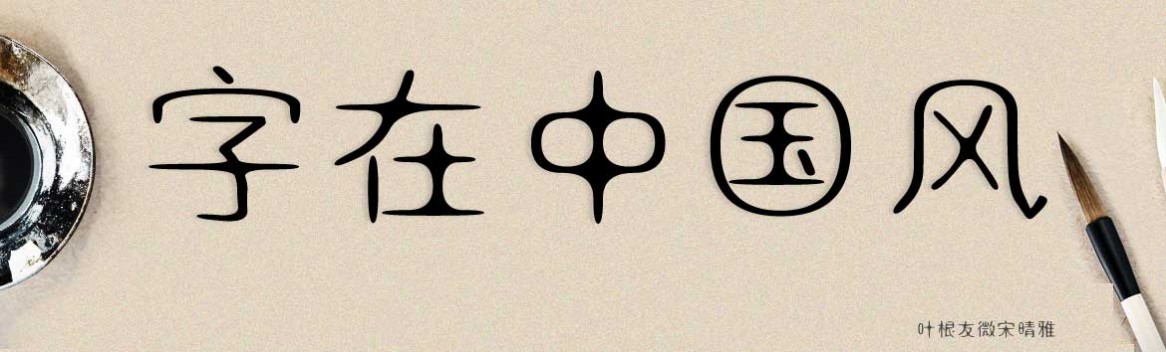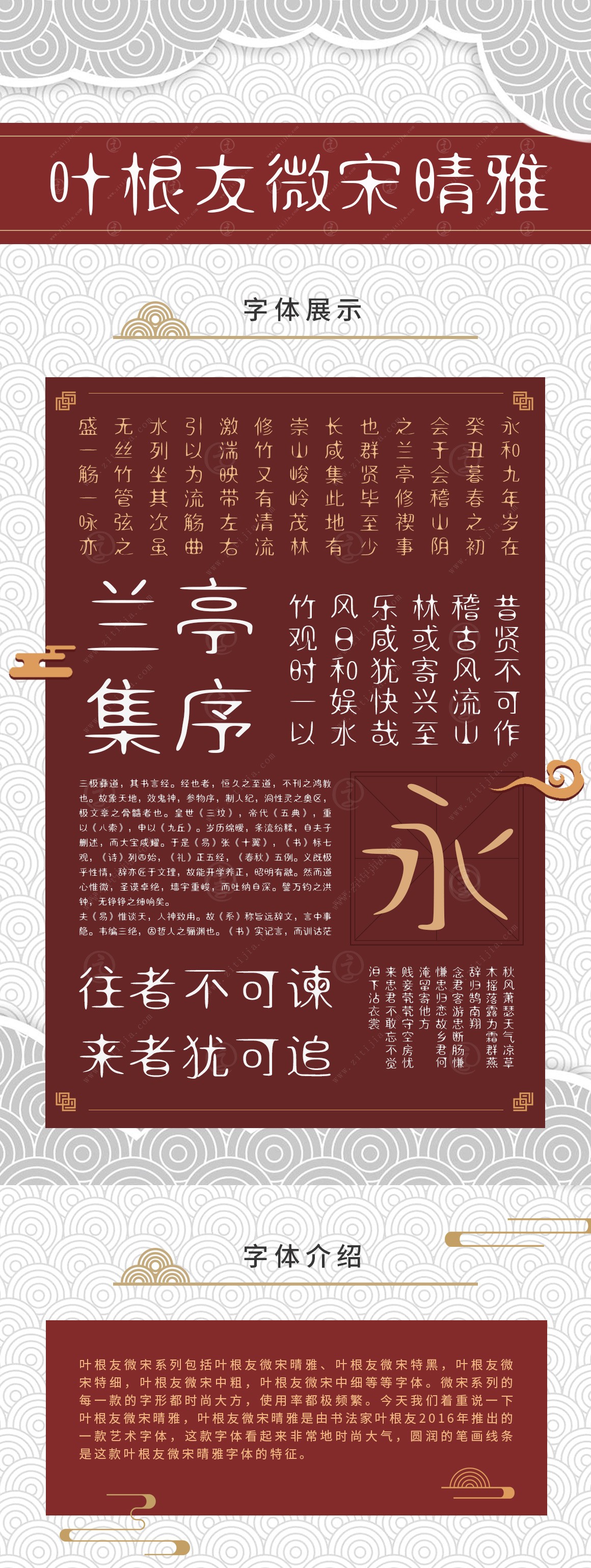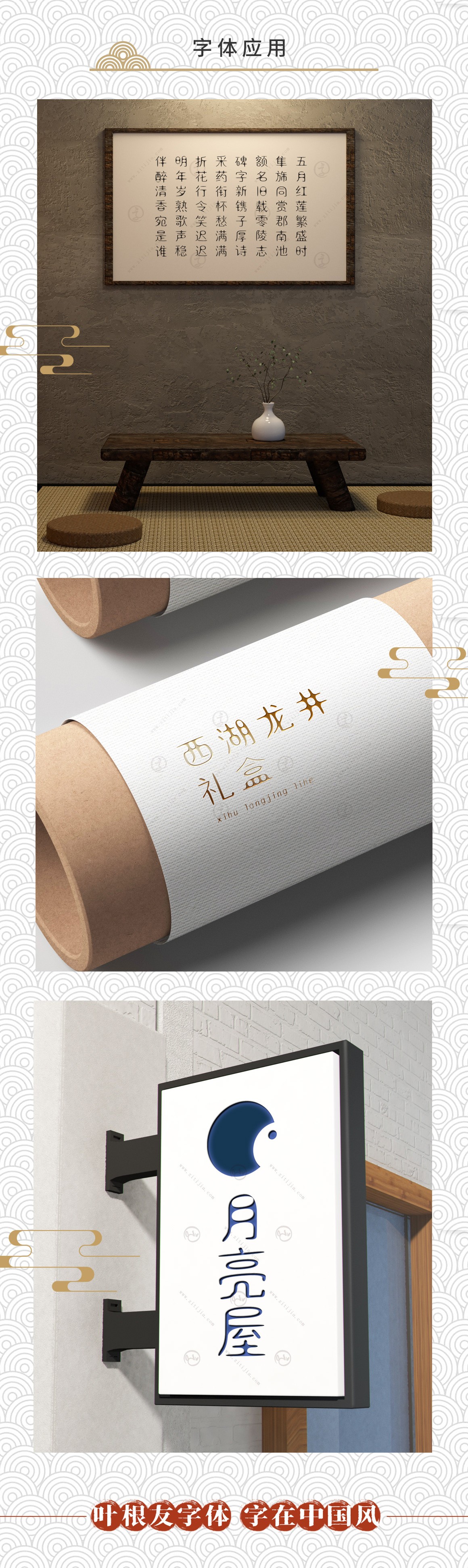
葉根友微宋晴雅
字體作者:葉根友
創(chuàng)作年代:2014年
字體字?jǐn)?shù):6763個(gè)中文漢字以及其他英文字母和阿拉伯?dāng)?shù)字
字體介紹
葉根友微宋晴雅是一款柔性的字體,比較適合內(nèi)文排版和追求時(shí)尚一族的應(yīng)用,圓潤(rùn)的筆畫(huà)線條是這款葉根友微宋晴雅字體的特征,希望大家喜歡。